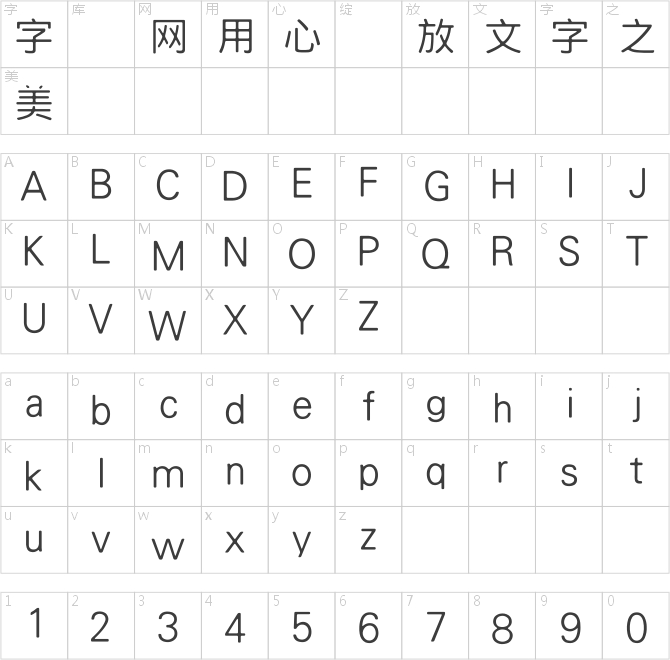
王漢宗細黑體繁 詳情頁
字體名稱: 王漢宗細黑體繁
王漢宗細黑體繁
王漢宗細黑體繁介紹
王漢宗細黑體繁字體字庫是一款讓人賞心悅目、百看不厭的中文字體,適合各類廣告和產(chǎn)品包裝設(shè)計應(yīng)用,字體大小6.28MB,格式為ttf字體,上傳用戶是后天的昨天,作者/版權(quán)方為王漢宗